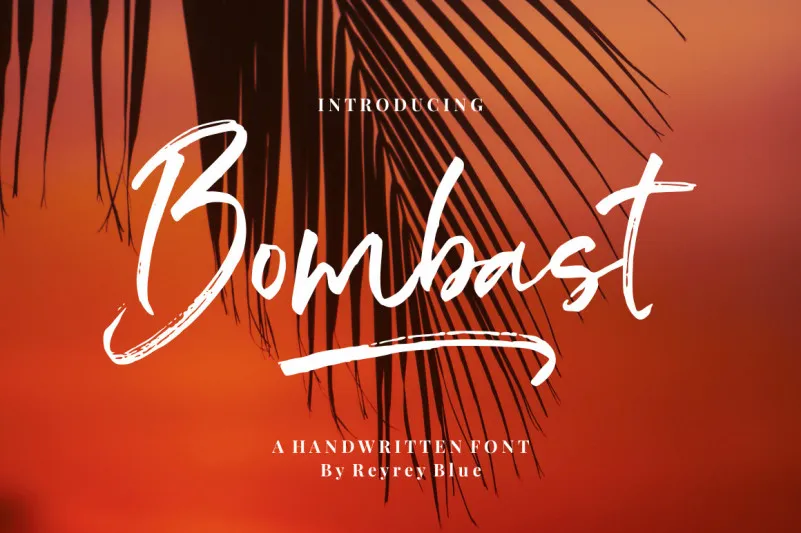
A Bombast Font é uma elegante fónta script, ideal para quem busca trazer uma cara nova às suas criações digitais. Seu estilo fluido e adaptável evoca um charme moderno, perfeito para dar vida a designs que precisam se destacar na atualidade. Essa fonte foi especialmente concebida para aqueles profissionais de design gráfico que buscam uma aparência fresca e sofisticada em seus trabalhos, dando-lhes liberdade para criar algo singular e único. Com seu ar de tendência, a Bombast Font é perfeita para designers que querem dar um toque distintivo às suas mensagens ou projetos digitais. Seja para editoriais, publicações online ou até mesmo para aplicar em logotipos e identidades visuais — esta fónta estará sempre ao seu lado, pronta para transformar qualquer design em algo realmente especial.